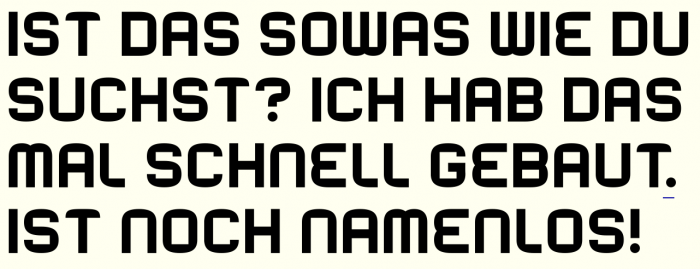
Eckig trifft rund – Schrift ähnlich CASA-Wortmarke gesucht
Hier noch eine ähnliche Richtung (links):
Gibt es noch weitere Vorschläge?
Es wäre eben schön, wenn die Außenkontur eher rund verläuft und die innere Kontur (Punzen) eine verleichsweise eckigere Anmutung aufweist, so dass die Strichstärke nicht mehr homogen ist.
Ich würde sie "Herberger inside out" nennen – das Eckige muss hier ins Runde, nicht umgekehrt ;-)
Also »Regrebreh«? 8-)
hm, inside out heißt doch "auf links gedreht", nicht "rückwärts". Oder lieg ich falsch?
Kommt wohl auf die Methode an. Stell dir vor, eine Faust stößt durch H, e, r etc., greift sich das letzte r und zieht es und seine (immer noch fest hängenden Nachbarbuchstaben) durch die gebrochene Bahn wieder nach links. Da wäre das Endergebnis doch irgendwie umgekrempelt. Wir dürfen nicht vergessen, dass die Welt der Zeichenketten eindimensional ist. Da sehen dann viele Prozesse anders aus als in unserer dreidimensionalen Welt. ;-)
Rueck gefällt mir aber auch.
So in der Art meinte ich das. :-) Kathrin würde jetzt sicher sagen: »Du bist ein Goldschatz!«
Ich brauchte das G das B und das U und habe mich auch mal fix daran versucht, aber bei Dir sieht das deutlich gekonnter aus! Aber das B hat es in sich, oder?
Interessant – und ich dachte von der Sorte gibt es inzwischen mindestens eine Hand voll. Vielleicht hätte ich auch einfach mal bei fonstruct stöbern sollen …
Also OK, The winner is: "Rueck" - allerdings müsste man das wohl mit einem Trema über dem e schreiben. Aber gerade die Kniffeligkeit der richtigen Aussprache hat mir gefallen, zuden schön kurz.
Die Schrift, obzwar eine reine Versalschrift hab ich schon recht komplett ausgestattet, sogar unseren Liebling, das Versal-ß ist drin.
Super! Allerdings fehlt der Rueck das charmante S, welches vom strengen Raster abweicht und dadurch der Wortmarke erst eine gewisse Eigenständigkeit verleiht.